vivo发布全新子品牌iQOO
2019年3月1日,著名手机品牌vivo正式对外发布了全新子品牌手机——iQOO。
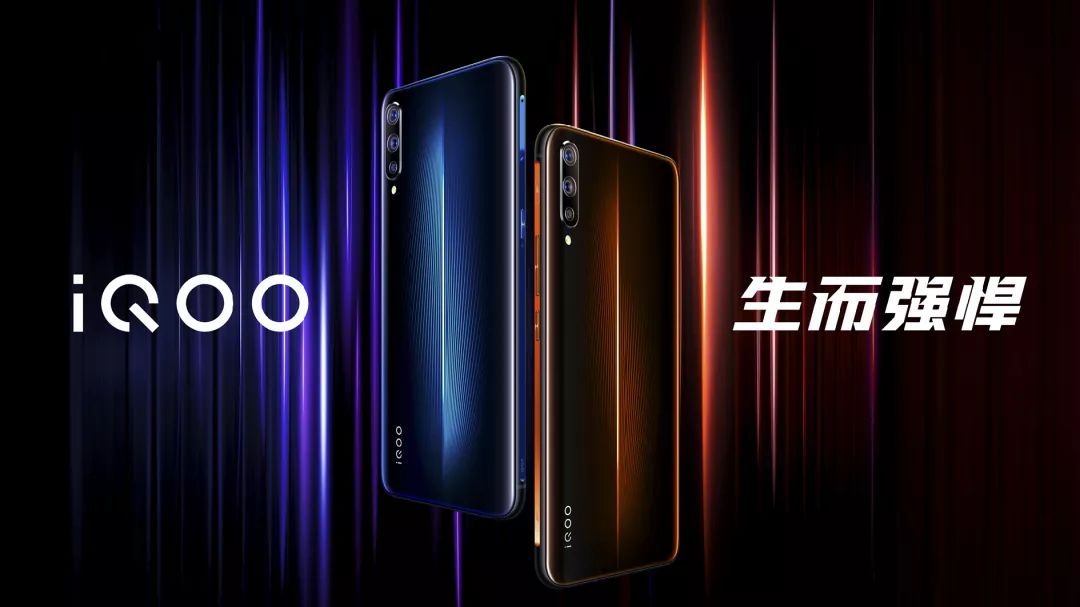
第一款iQOO产品是一款超强性能的高端游戏手机,7纳米工艺高通骁龙855处理器、12GB超大运存、超级液冷散热等多种高端配置,给用户带来前所未有的电竞级体验。
在当晚的新品牌发布会现场,iQOO的标志无处不在,分外惹眼,十足的强悍气场。
iQOO的品牌形象设计来自陈宋品牌顾问和vivo设计团队的合作。结合产品的极致性能与硬核外观,iQOO的产品被定位为:忠于高性能,为追求极致的互联网人群提供高价值的性能科技产品。
iQOO品牌名字来自于“i Quest On and On”的缩写。纯英文的字体标志,有助于让用户形成国际化的品牌印象,也方便向海外市场拓展。
iQOO的产品特征“强悍的Intrepid、极速的Top-Speed、赋能感的Empowering、能量的Powerful”成了设计发想的开端。
经过多番提案与沟通,最终标志终于打磨完成。标志首字母“i”是由两个方形结合,棱角分明的形状表达对性能的高度追求,上下规整秩序的摆放显示了iQOO理性的态度。
“Q”、“O”、“O”的圆形设计,展现了iQOO的能量与动感,同时也增添感性的魅力。字母“Q”的分离式设计,既体现了速度感,又为品牌后续的延展提供更多的可能性。
品牌LOGO醒目粗重,具有稳重、大方、强有力的视觉语言,彰显大品牌魅力。
品牌的应用设计与广告有所不同,整体采用的是黑色,这让品牌更增添一种神秘的能量。
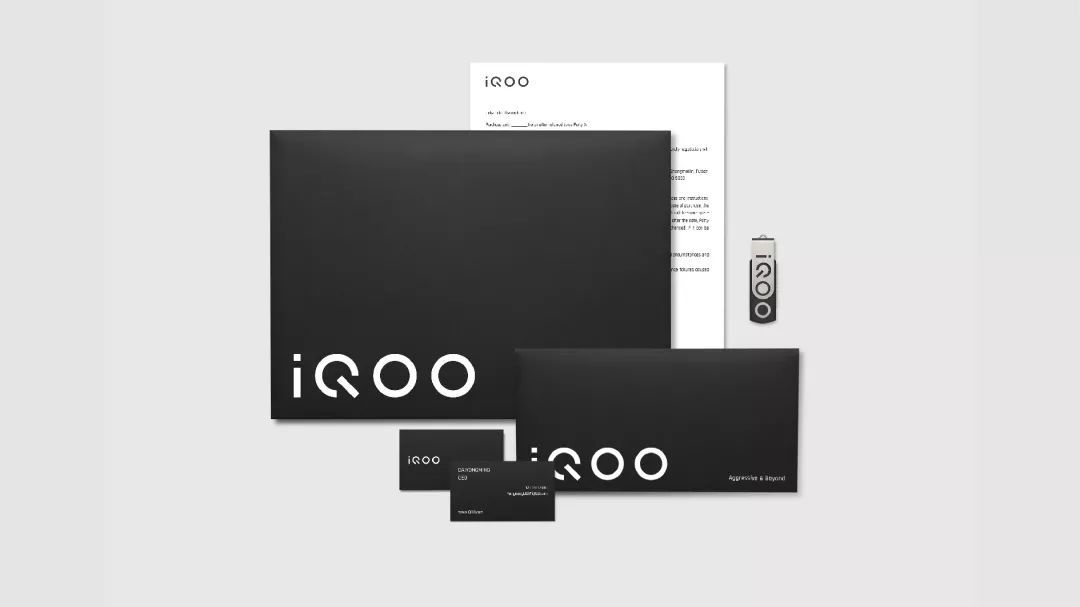
在iQOO的官网上的页面是这样设计的: